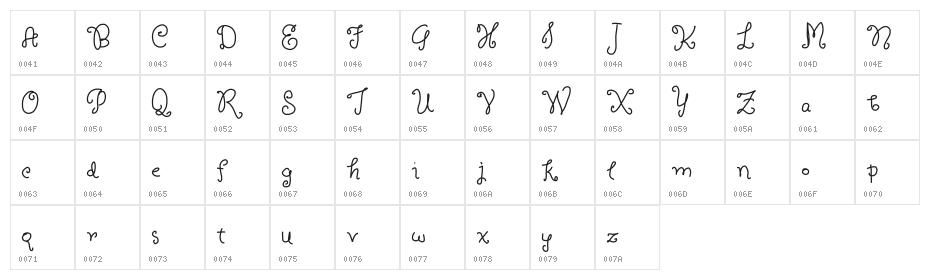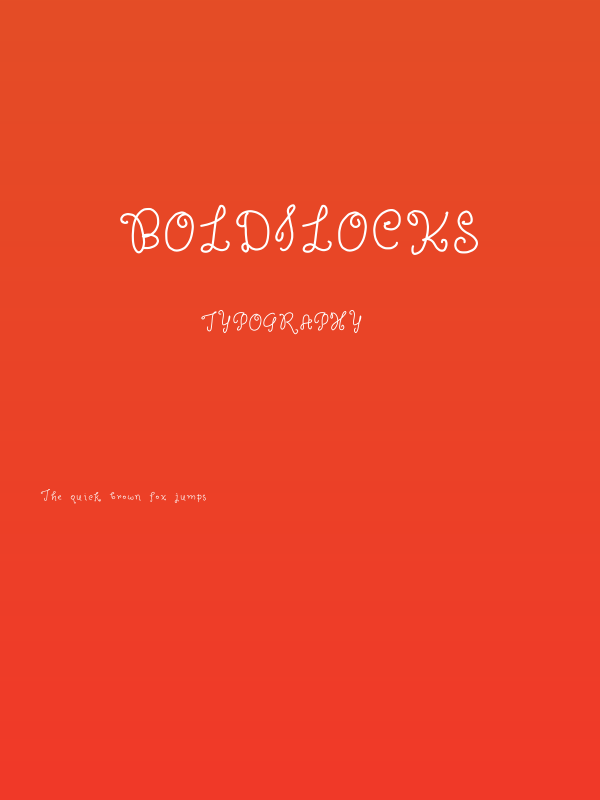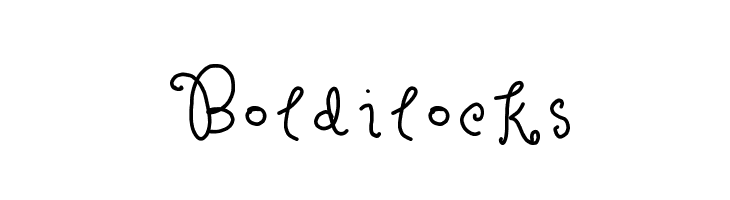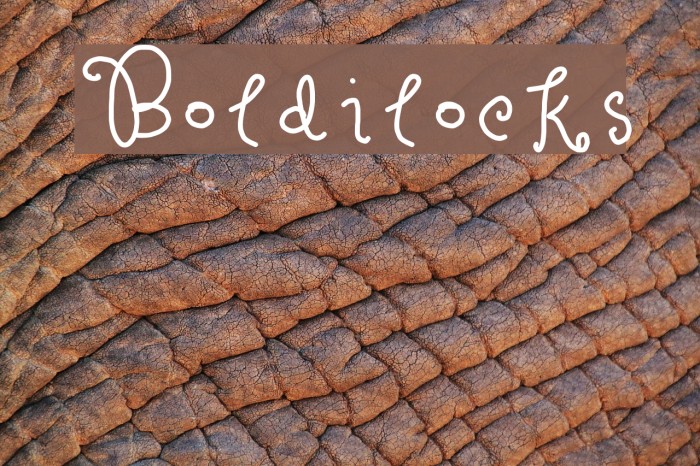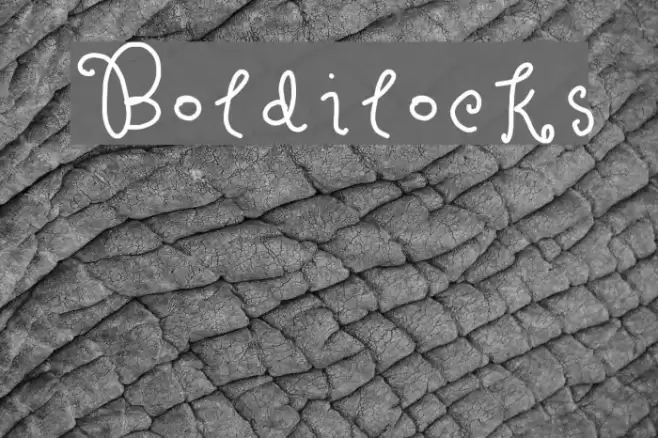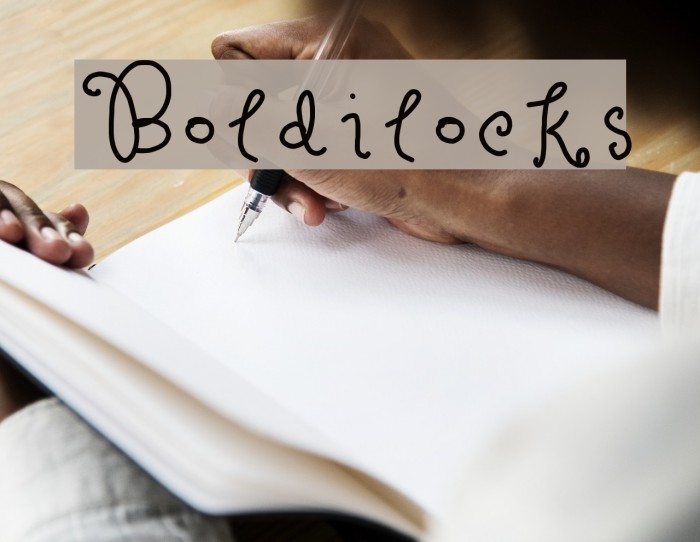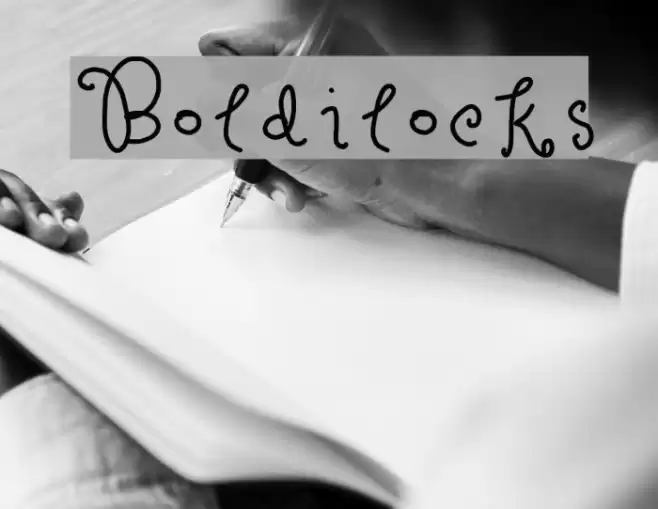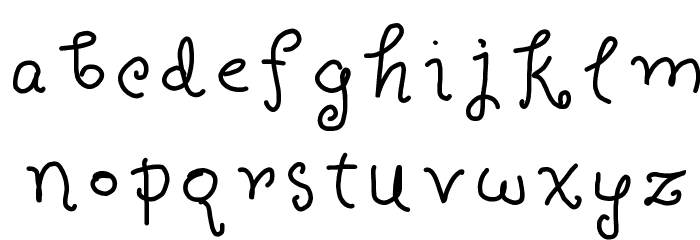
Boldilocks Font
| Cas d'utilisation | Logos, Headlines, Creative projects |
| Projets proposés | Ideal for greeting cards, children's books, playful branding, and creative invitations. |